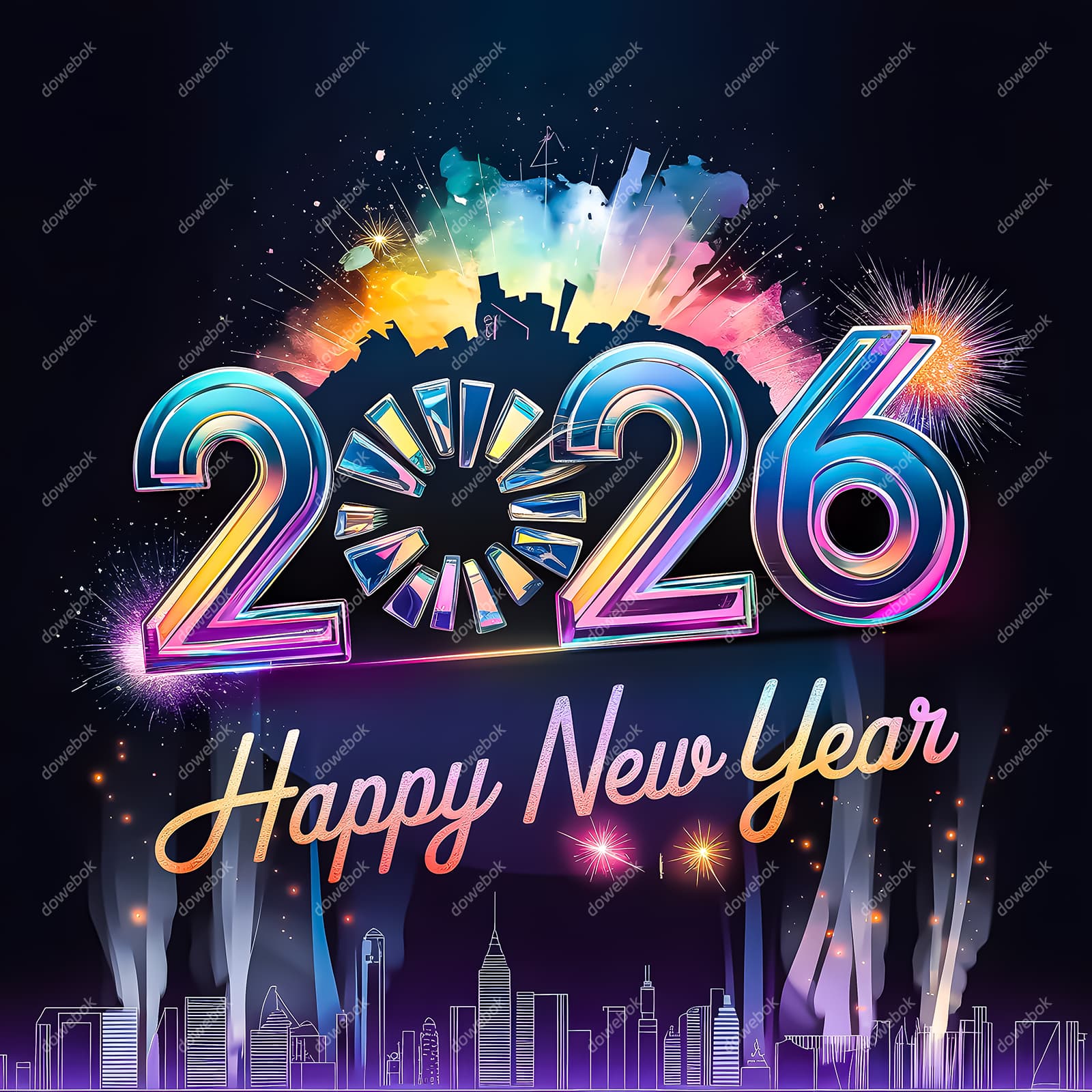
这是一款城市剪影和绚丽数字设计 2026 新年快乐素材,深黑夜空下,“2026” 以镭射渐变质感呈现,蓝粉光泽亮眼吸睛,数字间嵌着放射状装饰。背景是彩烟、烟花与城市剪影,营造出都市跨年的热烈氛围,下方花体 “Happy New Year” 添了柔美感。整体以炫彩元素 + 都市夜景,既显跨年的新潮动感,又透出盛大热闹的节日张力。